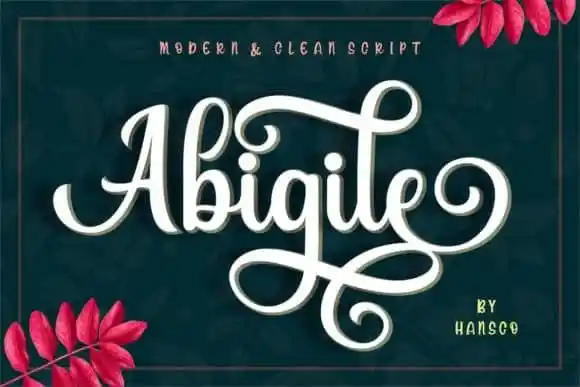
Abigile Calligraphy Font – Fonte Grátis
Abigile Calligraphy Font
A fonte Abigile Calligraphy é uma elegante escolha para aqueles que procuram um estilo de escrita delicado e bem equilibrado. Ela não apenas oferece beleza aos caracteres, mas também a característica de se adaptar a uma ampla variedade de designs. Feita pelo font designer HansCo da plataforma 99designs, esta é uma moderna fonte à mão cheia que foi cuidadosamente criada para torná-la um verdadeiro favorito. Com seu charme casual e beleza natural, o Abigile se destaca tanto no uso de fundos ativos quanto como a capa de um título isolado. Suas qualidades fofas contribuem para uma aparência amigável e leitura fácil, resultando em uma fonte extremamente versátil que se adaptará perfeitamente em qualquer contexto. O Abigile é uma escolha ideal tanto para trabalhos profissionais quanto para projetos pessoais, tornando-o um recurso indispensável para a sua biblioteca de recursos gráficos.